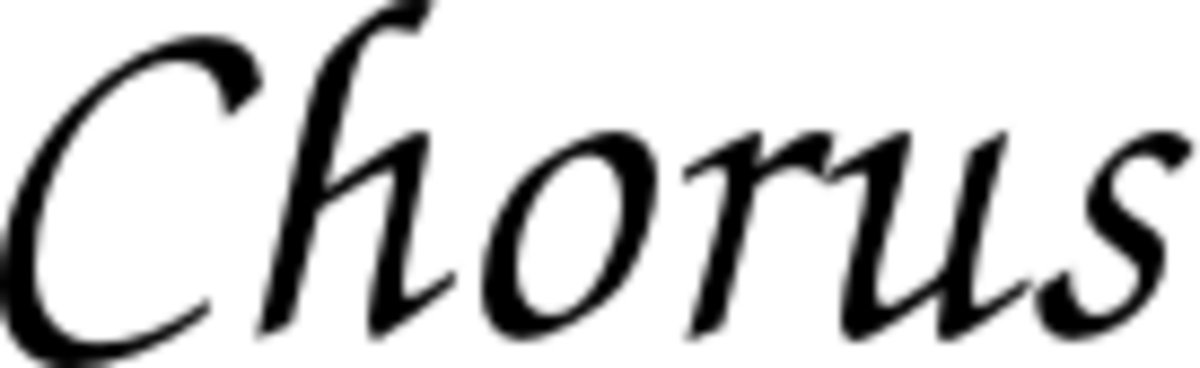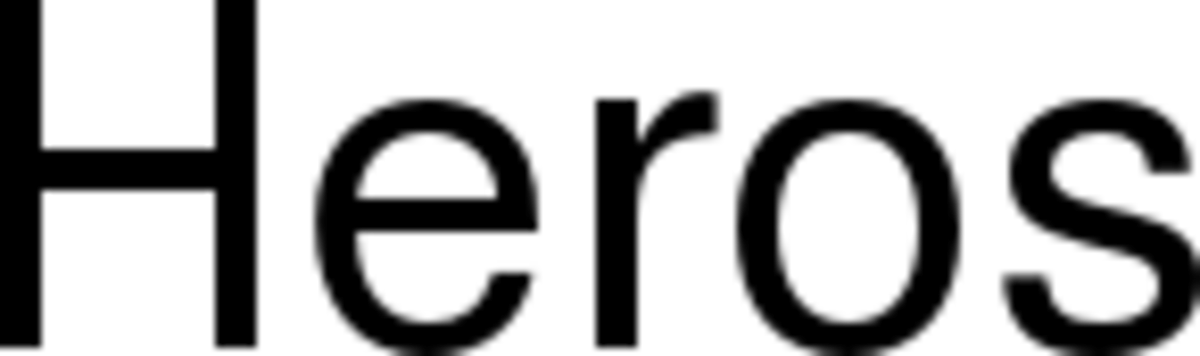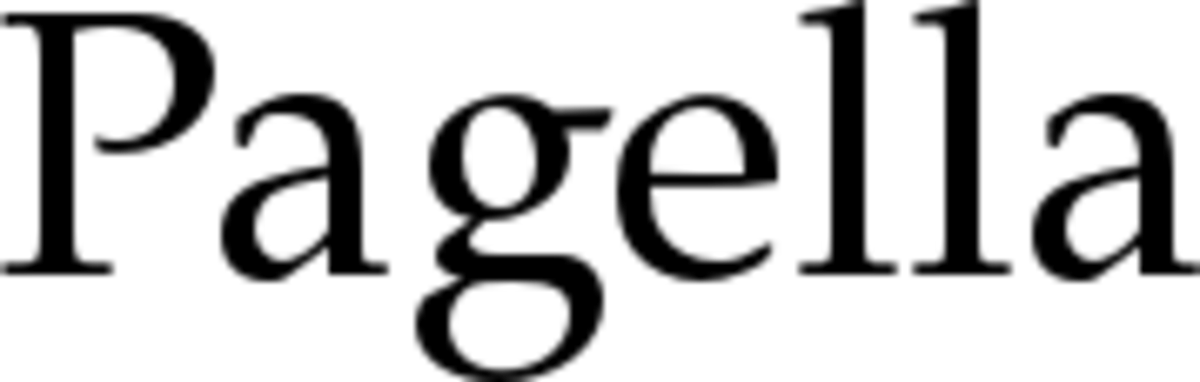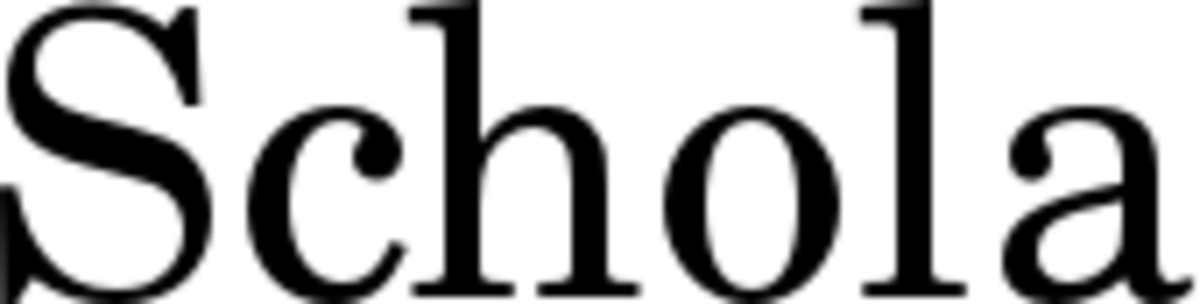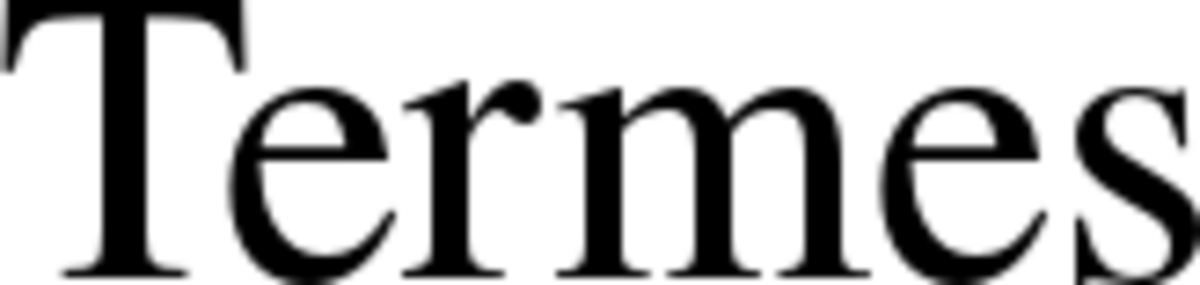
Eccoci come promesso a parlare di un tema molto importante, ma spesso sottovalutato da tutti: i Font, o caratteri tipografici.
Probabilmente alcuni di voi da piccoli hanno giocato a scrivere storie più o meno orribili sul computer.
Wordpad, una pagina e mezza se andava bene, tempi verbali volanti e l’immancabile font a 18pt, meglio se verde foresta, tipo Viner Hand ITC — o Tempus Sans ITC — per dare quell’idea di “Ehi! Mi ci sto impegnando! Guarda, ho scelto addirittura un font figo! Mica come quelli noiosi dei libri!”.
Ok, più di quanto non pensassi, ma il punto rimane:
Chi di voi, da allora, ha più degnato di uno sguardo i font? Quanti si sono accontentati del Times New Roman o dell’Arial, o delle nuove alternative firmate Windows, che immancabilmente trovate preimpostate nel vostro Office piratato? Alzate la mano.
Tanti, troppi di voi, non si fermano nemmeno a pensare a che font usano, e magari si ritrovano a scrivere la tesi per l’università senza averlo mai fatto.
A me successe proprio così e, se per la tesi non mi preoccupai troppo — tanto l’avrebbero letta solo tre vecchi professori ammuffiti che usano sempre Times New Roman — per la seconda tesi e per l’impaginazione del romanzo mi preoccupai un pochino di più.
Passando da Windows a Linux, però, i font cambiano, e la mia lunga ed estenuante ricerca e selezione certosina tra i font standard di Office venne meno.
Quindi ciò che vi proporrò oggi sono font professionali, che potrete usare senza paura su qualsiasi sistema operativo, e che si comporteranno magnificamente sia sullo schermo che in stampa. Per adesso ci fermeremo ad alternative gratuite per i font più usati, non voglio dilungarmi troppo con altri tipi di font, ma ne riparleremo.
Ora veniamo ai font:
1. GUST e-foundry
Questo progetto nasce nel ‘92, con l’intenzione di promozionare il sistema tipografico TeX in Polonia, ma la loro intera storia è in polacco, e non so voi, ma io non parlo polacco. La cosa che ci importa è che questi meravigliosi esseri umani hanno preso e ampliato e modificato e pubblicato gratuitamente dei font precedentemente liberati dalla URW++, altra e-foundry — ovvero fabbrica elettronica.
La loro famiglia di font Tex Gyre è perfetta per ogni utente, e fornisce 8 font che ricalcano alcuni dei principali font a disposizione in sistemi operativi Windows, però che con licenza free.
Andiamo a vederli:
Tex Gyre Adventor è un’alternativa libera al font Avant Garde Gothic, ma anche a Futura e Century Gothic.
Adatto a titoli e grafica minimalista o con gusto retro. Questo font ha segnato la storia e, se fate un po’ attenzione quando camminate o leggete, lo noterete spesso…
Tex Gyre Bonum è un’alternativa libera al font Bookman ITC e Bookman Old Style.
Font adatto alla stampa di un libro, bello grosso e tozzo, anche se tende a occupare molto spazio.
Libro per bambini, forse?
Tex Gyre Chorus è un’alternativa libera al font ITC Zapf Chancery e più in generale ai font calligrafici.
Non mi sono mai piaciuti, ma visto che c’è ve lo propongo.
Tex Gyre Chorus è un’alternativa libera al font Courier e Courier New.
Il font che imita la scrittura a macchina, può sempre essere utile (vedasi il banner questo blog, anche se il font non è questo qui, bensì questo).
Tex Gyre Chorus è un’alternativa libera al font Helvetica e Arial.
I più comuni dei font Sans Serif, o bastoni, o caratteri senza grazie. Risultano molto leggibili sui display moderni, motivo per cui quasi ogni sito esistente ne fa uso.
Tex Gyre Chorus è un’alternativa libera al font Palatino.
Questo è uno dei miei font preferiti, e finalmente ne trovo una versione gratuita. Ottimo per stampare qualsiasi tipo di documento, tesi, romanzi, libri, contabilità (???)…